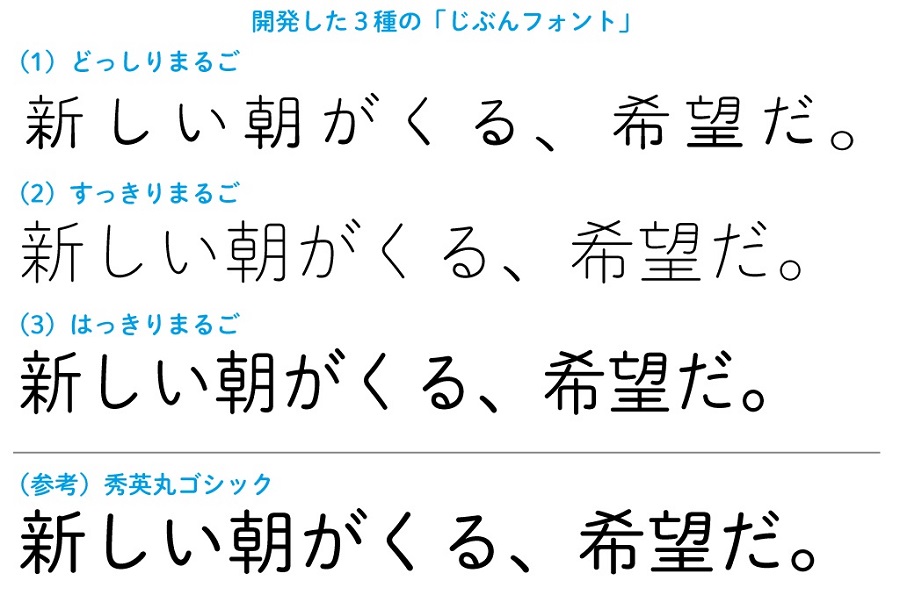
ディスレクシアを含む文字の読み書きに困難がある人に見やすく読みやすいフォント「じぶんフォント」
大日本印刷(DNP)は、東京工業大学、ファシリティジャポン、リアルタイプと連携し、ディスレクシアを含む文字の読み書きに困難がある人にも見やすく読みやすい「じぶんフォント」のプロトタイプを開発したこと2022年9月26日に発表した。
また、開発した「じぶんフォント」の読字体験ができ、多様なフォントと比較しながら、自分に合うフォントを見つけられるWebサイトも公開。
さまざまな利用者からの意見を収集して、「じぶんフォント」の改善や社会実装、さらなる研究開発を目指していくようだ。
「じぶんフォント」開発の背景
ディスレクシアは、知的能力に関係なく文字を読むことが困難な学習障がいであり、日本では学齢期児童の約8%*1、英語圏では約10~15%*2にこの症状があると言われている。
ディスレクシアの人にとっては、フォントの変更が読み難さの軽減に役立つ場合があることが知られており、欧米では、ディスレクシア対応フォントに関する研究が進み、実用化されている。
国内でも朱助教によるディスレクシア対応の日本語フォントの試作・評価が進んでおり、その有用性が確認されている。
一方、日本語の情報処理で少なくとも必要とされる約7,000字(JIS第1・第2水準)のフォントの開発には、高い負荷がかかっていた。
こうした課題の解決に向けてDNPは、秀英体の開発で培ったノウハウを活かして「じぶんフォント」の開発を開始し、朱助教、Webアクセシビリティ技術を有するファシリティジャポン、フォント開発やWebフォントの配信技術を有するリアルタイプとの連携による「じぶんフォントプロジェクト」を結成した。
「じぶんフォント」の特長
1.“読み書き困難”の特性に合わせた、3種類の形状のフォントを開発
“読み書き困難”の症状はさまざまであり、「文字が躍る・動く・ねじれるように感じてしまい、どこにどの文字があるか分からない」「文字や単語の間が広い場合には読めるが、字間が狭いと誤りが増える」など、人によって症状が異なる。
朱助教は、文字の読み書きに困難がある人の協力のもと、自身が開発したフォントの評価・分析を行い、(1)文字の下部が太い、(2)全体が細め、(3)全体が縦長で太め、といった3つの傾向のあるフォントが好まれることを発見した。
今回の「じぶんフォント」の開発に当たっても、これらの特徴を活かした形状とした。
2.秀英丸ゴシックをベースに開発した手書きに似たゆとりがあるフォント
「じぶんフォント」は、画線がシンプルで、先端や角が丸い「秀英丸ゴシック」をベースに開発している。
「じぶんフォント」のひら仮名は、形状や大きさを整え過ぎないようにしており、例えば「い」は平たく、「く」は縦に長くなど、手書きの形状に近いデザインで、字間にゆとりがある。
これらの特徴は、読み書きに困難がある人に好まれる形状であることが、朱助教の研究で判明している。
「じぶんフォント」のコンセプトと読字体験Webサイトの立ち上げについて
文字の読み書きに困難がある人も含め、多様な見え方を持つ全ての生活者にとって読みやすく、一人ひとりに合ったフォントを提供したいという想いから、「じぶんフォント」と名付けて開発した。
4社の共同プロジェクトでは、多様な見え方の特性を持つ人々の協力を得て、より見やすく読みやすいフォントの開発・実用化に取り組んでいる。
実用化に向け、誰でも「じぶんフォント」の読字体験ができ、多様なフォントと比較しながら、自分に合うフォントを見つけられるWebサイトも公開。
サイト上でアンケートを実施し、その結果から研究を進め、開発フォントのブラッシュアップを図っていく。
「じぶんフォント」今後の展開
DNPは「じぶんフォントプロジェクト」に参加する大学・企業とともに、「じぶんフォント」の評価と改善を繰り返し、より有用なフォントを開発する他、ユーザーが自分の読みやすい文字の形へ自由にカスタマイズできるフォントの開発や普及にも取り組む。
また、高齢者・情報弱者・非母語話者等にも配慮したコミュニケーション支援の技術やサービスの開発も進め、「DNPグループ行動規範」の一つに掲げている、多様な人々が暮らしやすい「ユニバーサル社会の実現」を目指していく。